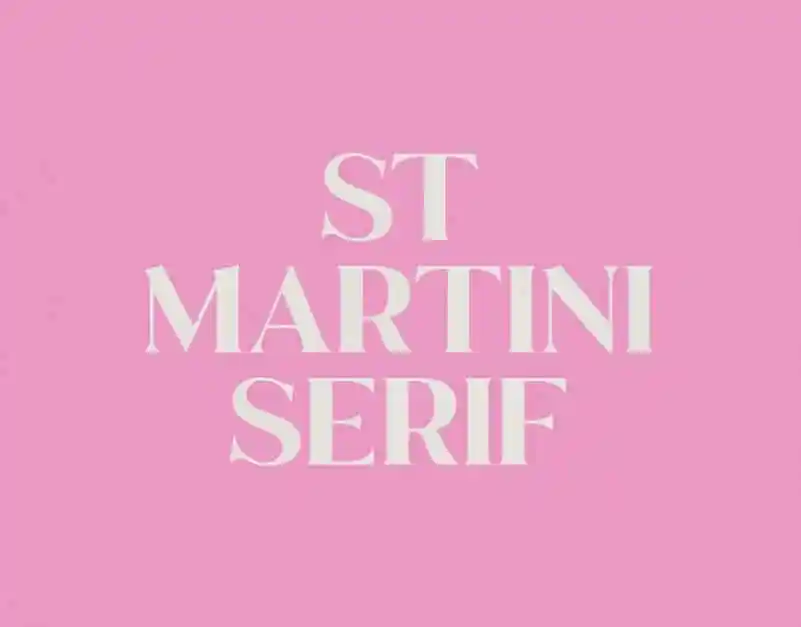
A St Martini Serif Font é uma tipografia moderna e elegante com detalhes únicos criados pelo font designer Graham Paterson. Este tipo de letra se destaca especialmente quando usada em grande tamanho, sendo ideal para headlines ou títulos. Você pode apreciar a beleza detalhada em cada caractere, o que tornará sua utilização mais fashionista e vibrante. Perfeito para ambientes onde você deseja destacar o texto, seja de forma criativa ou como um acréscimo elegante ao design. Seja para uma apresentação poderosa, um site profissional ou até mesmo um anúncio impactante, a St Martini Serif Font é a escolha perfeita para deixar seu trabalho mais chamativo e imponente.